OCR-Schriften
Terminus aus der Informatik (Computer Science) für alphanumerische Antiqua Schriften mit einer stark stilisierten Typometrie für die automatisierte optische Zeichenerkennung durch Codiergeräte oder Computer; maschinenlesbare Schriften. OCR steht für eng. »Optical Character Recognition«, eine Methode für die automatisierte »Optische Zeichenerkennung« innerhalb von Bildmotiven.
Die erste OCR-Schrift, die OCR-A, wurde 1968 im Auftrag der US-amerikanischen Regierung entwickelt. Sie ist eine Normschrift, die in der ANSI INCITS 17-1981, 1) DIN 66008 2) und ISO 1073-1 3) spezifiziert ist.
Da die Elektronische Datenverarbeitung (EDV) gescannte Texte als Grafiken wahrnimmt, basieren OCR-Schriften auf dem Prinzip der Mustererkennung. D.h., einzelne Buchstaben, Ziffern und Satzzeichen werden zuerst aus einem Gesamtmotiv, z.B. einem Reisepass oder einer ID-Card, extrahiert, um die Textinformation anschließend in einer textbasierten Software weiterverarbeiten zu können. Dazu vergleicht eine Software die einzelnen Zeichenmuster einer OCR-Schrift mit einer im System hinterlegten Mustermaske und erzeugt dann den jeweiligen Buchstaben bzw. das Satzzeichen.
Die ersten Anwendungen der OCR-A Schrift waren beispielsweise für die automatische Verarbeitung von gescannten Pässen, ID-Cards, KFZ-Zeichen oder Scheckformularen gedacht.
1973 entwickelte die European Computer Manufacturers Association (ECMA), eine privatwirtschaftliche internationale Normungsorganisation zur Normung von Informations- und Kommunikationssystemen und Unterhaltungselektronik mit Sitz in Genf, 4) die OCR-B, die der Schweizer Schriftgestalter Adrian Frutiger (1928–2015) gestaltete. Diese OCR-Variante verfügte im Gegensatz zur OCR-A über eine natürlichere Typometrie und war nicht mehr so künstlich stilisiert. Die OCR-B ist ebenfalls eine Normschrift, die in der DIN 66009 und in der ISO 1073-2 spezifiziert ist.
Sowohl die OCR-A wie auch die OCR-B sind dicktengleiche Schriften und verfügen über ein Majuskeln und Minuskeln sowie Arabische Ziffern.
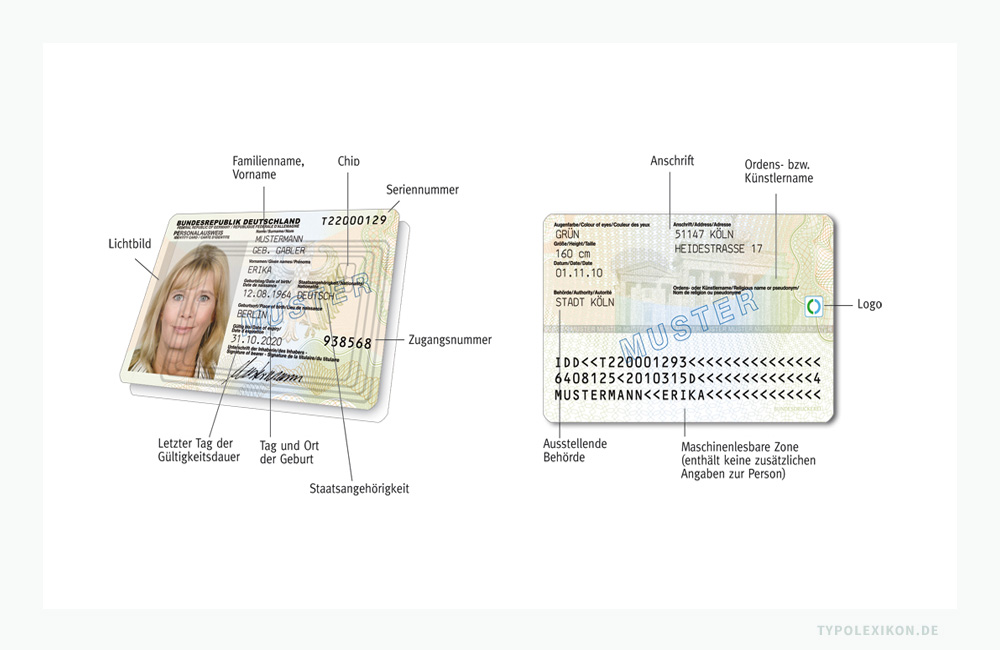
Bei Banken und Behörden kam kurzeitig auch eine OCR-H, eine Referenzschrift für handgeschriebene Blockschriften im Rahmen vorgegebener Felder von Formularen zur Anwendung. Die OCR-H war ebenfalls eine genormte Schrift, die in der DIN 66225 spezifiziert wurde. Sie verfügte nur über Majuskeln und Arabische Ziffern.
OCR-Schriften haben in der datenverarbeitenden Bürokommunikation ihre ursprüngliche Anwendung aufgrund moderner Technologien weitgehend verloren, da heute nahezu alle Schriften, auch Handschriften, mittels OCR-Software dekodiert werden können.
Bei amtlichen Reisepässen, Personalausweisen, Führerscheinen oder beispielsweise bei Bankkreditkarten werden OCR-Schriften in speziellen »maschinenlesbaren Zonen« (MRZ) weltweit zum einheitlichen optischen Auslesen bis heute verwendet.
Heute versteht man unter »OCR« Optical Character Recognition primär eine Software für die schriftunabhängige Texterkennung.